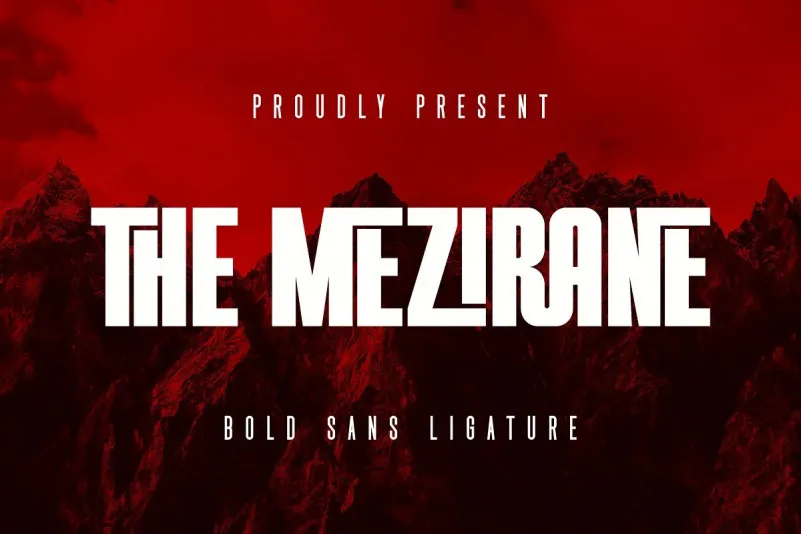
THE MEZIRANE Font – Fonte Grátis
THE MEZIRANE Font
A MEZIRANE Font é uma escolha inovadora para quem busca uma mistura perfeita de modernidade e originalidade em seu design visual. Criada por Almarkha Type, essa linhagem de tipo sans-serif traz à tona a energia vibrante que o nome sugere. Inspirada na tipografia de posters esportivos icônicos, foi desenvolvida para destacar-se no campo do design gráfico contemporâneo. Suas linhas robustas e densidade são tão impressionantes quanto suas ligaturas criativas, conferindo ao tipo uma aparência única e inconfundível. A MEZIRANE é o selo de sua autenticidade e modernidade, adaptada para atender a um leque diversificado de projetos design, desde posters urbanos até elementos gráficos em revistas digitais. Com seu charme distintivo, ela se destaca como uma opção confiável para estilos futuristas ou vintage contemporâneo.